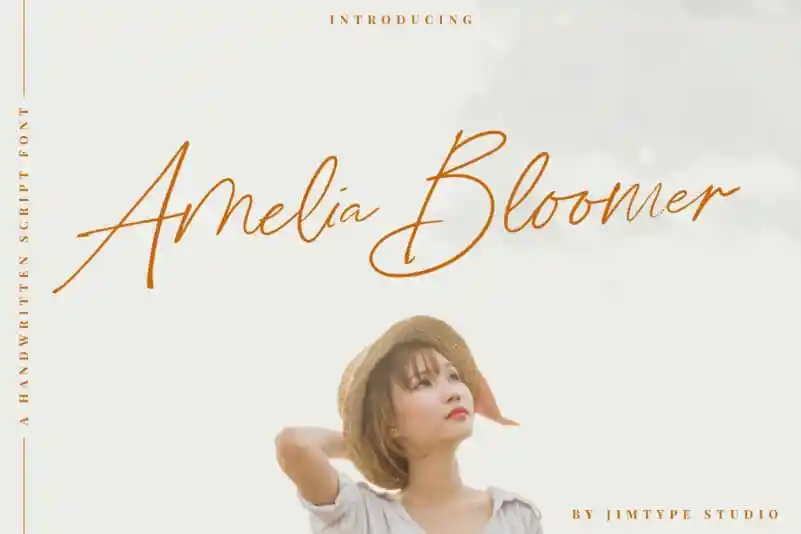
Amelia Bloomer Handwritten Font – Download Grátis
A Amelia Bloomer Handwritten Font é uma elegante fonte escrita à mão que traz estilo a qualquer projeto. Com acesso fácil a todos os glyphes e swashes por meio do PUA (Pre-defined User Access) codificado, este font permite que você crie designs impecáveis. Perfeita para aqueles projetos onde deseja expressar uma personalidade única através da escrita à mão, essa font encanta seus usuários e eleva suas criações ao nível mais alto. Com seu ar descontraído e delicado, a Amelia Bloomer Handwritten Font é perfeita para design gráfico, especialmente em seios de cartões de felicitações, logotipos e layouts pessoais. Sua facilidade de uso permite que você crie designs memoráveis, tornando sua fonte uma escolha inteligente para qualquer designer que busca um toque especial em suas criações.